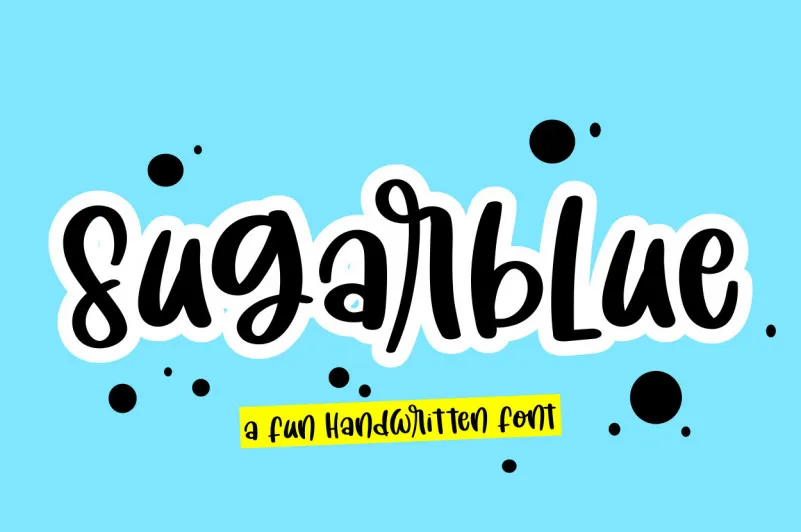
Sugar Blue Font – Fonte Grátis
Sugar Blue Font
A Sugar Blue Font é uma elegante escolha para designers que buscam uma fonte moderna e confortável. Essencialmente uma fonte script, ela carrega consigo nuances de elegância com sua curvatura suave e harmonia na tipografia. Com um design fluido, essa fonte permite criar textos graciosos e sutis, perfeitamente adaptáveis a uma variedade de aplicações – desde cartões de aniversário até designs de websites responsivos. A designer sugiharto1790 trouxe ao mundo Sugar Blue Font, uma escolha intuitiva para qualquer projeto que valorize um design delicado. Seja você um estudante de arte digital ou uma profissional freelance criando materiais visuais, essa fonte é perfeitamente adaptável às necessidades e estilo de seu trabalho. O uso desta fonte é simples e conveniente, com todas as facilidades para personalização e aplicação apropriadas. Com Sugar Blue Font na sua coleção, você pode criar um texto que não só seja funcional mas também capaz de dar o tom ao seu design, desde uma carta pessoal até um site corporativo sofisticado. Instale-a agora e experimente como ela pode enriquecer seus trabalhos!